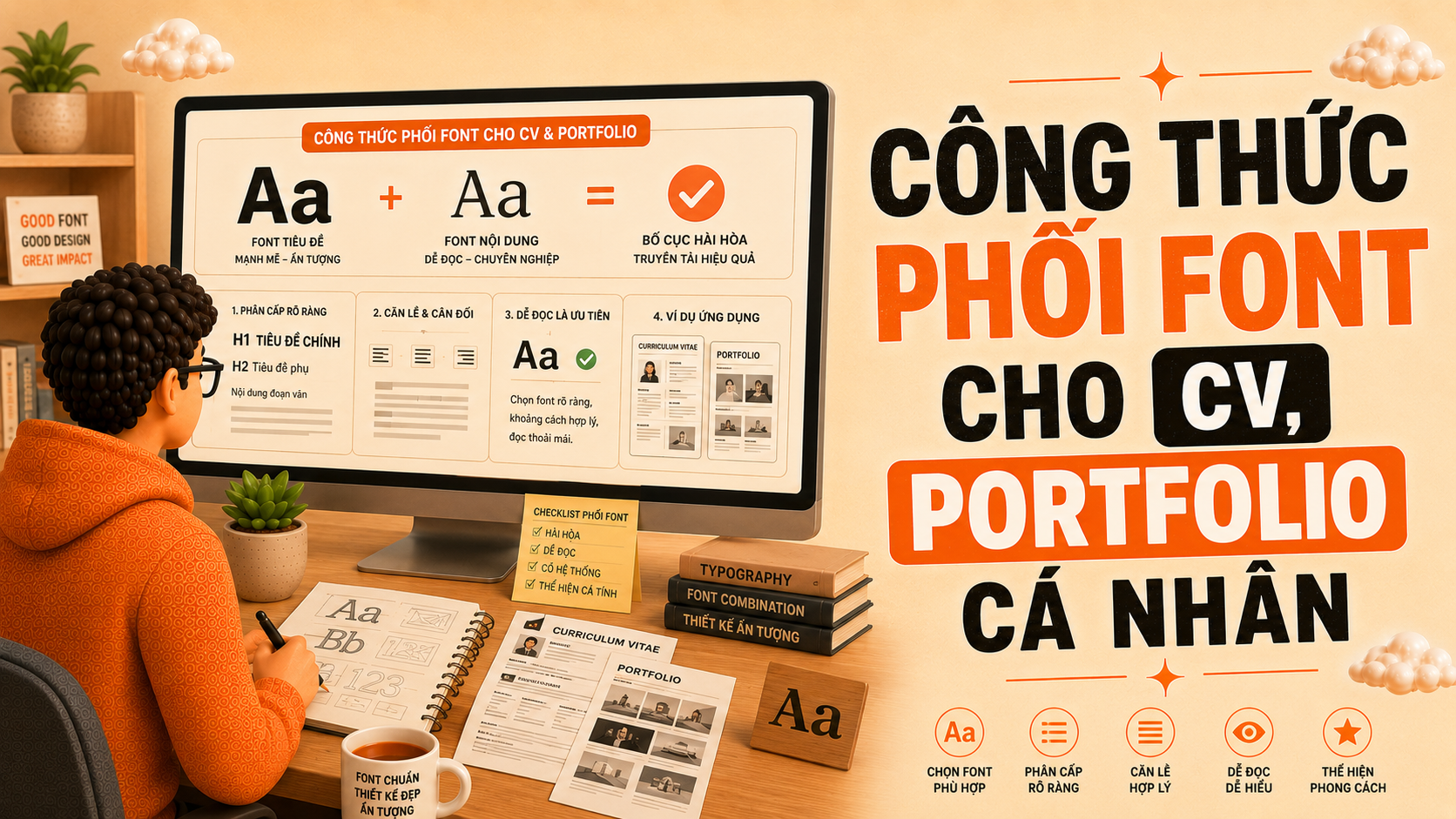
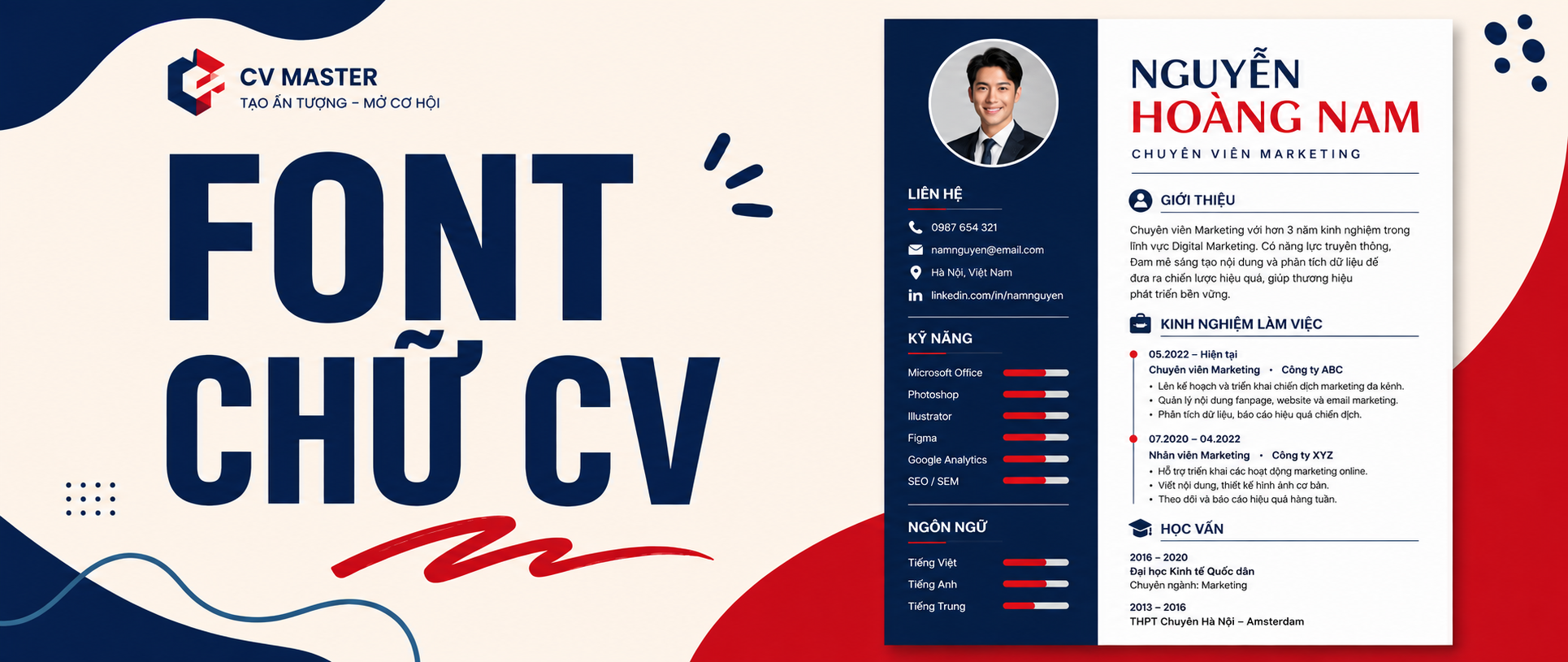
CV và portfolio cá nhân là nơi font chữ ảnh hưởng trực tiếp đến ấn tượng đầu tiên. Nhà tuyển dụng, khách hàng hoặc đối tác thường chỉ mất vài giây để quét tên, vị trí, kinh nghiệm, kỹ năng và các dự án nổi bật. Nếu font khó đọc, quá trang trí hoặc thiếu phân cấp, hồ sơ có thể bị đánh giá kém chuyên nghiệp dù nội dung rất tốt.
Font chữ cho CV, portfolio cá nhân cần cân bằng hai mục tiêu: rõ ràng để người đọc nắm thông tin nhanh, và có cá tính để hồ sơ không bị giống mẫu đại trà. Với CV ứng tuyển, font nên sạch và đáng tin. Với portfolio sáng tạo, font có thể mạnh hơn ở tiêu đề. Với profile chuyên gia, font cần tinh tế và có chiều sâu. Với website cá nhân, font phải đọc tốt trên nhiều kích thước màn hình.
Bài viết này gợi ý các font Việt hóa trên Font S99 phù hợp cho CV xin việc, resume, portfolio designer, hồ sơ freelancer, profile cá nhân, PDF dự án, media kit, website cá nhân và personal branding. Mỗi font được trình bày riêng một dòng kèm anchor Tải về để bạn dễ tải xuống và thử ngay vào thiết kế.
Điểm cần nhớ là CV và portfolio không phục vụ cùng một hành vi đọc. CV thường được quét nhanh để lọc năng lực. Portfolio được xem kỹ hơn để đánh giá gu, quy trình và kết quả. Vì vậy, một bộ font tốt nên có font nền thật rõ cho thông tin, đồng thời có font nhấn đủ cá tính cho phần thương hiệu cá nhân.
Một CV tốt không chỉ đẹp. Nó phải giúp người đọc tìm thấy thông tin quan trọng: bạn là ai, ứng tuyển vị trí gì, có kinh nghiệm nào phù hợp, kỹ năng chính là gì, dự án nào đáng chú ý và cách liên hệ ở đâu. Font đóng vai trò như hệ thống dẫn đường cho mắt.
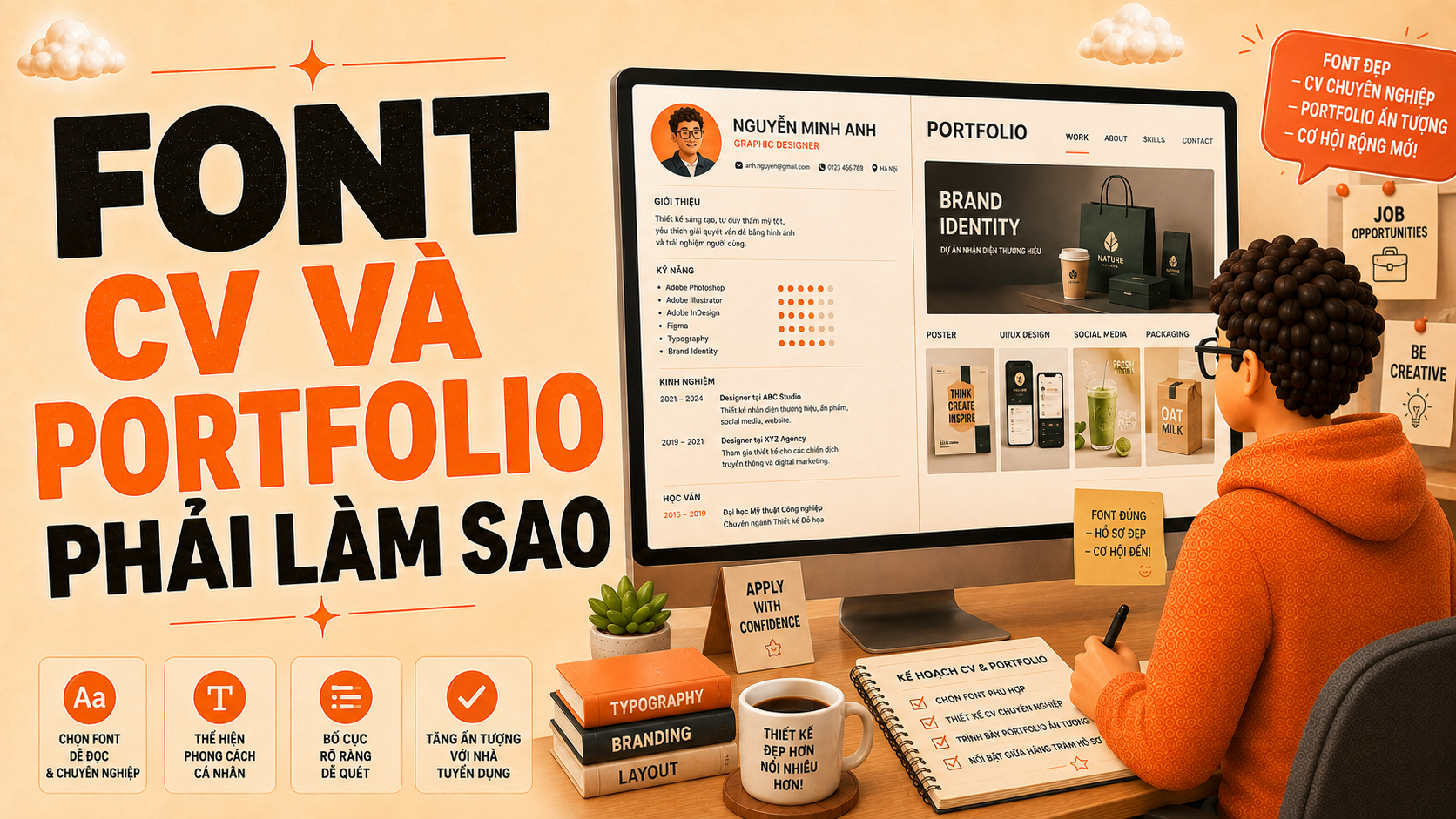
Portfolio cũng vậy. Người xem không đọc từng chữ ngay từ đầu. Họ lướt qua cover, mục lục, case study, ảnh dự án, vai trò của bạn, kết quả đạt được và phần liên hệ. Nếu font tiêu đề thiếu lực, portfolio mất điểm nhấn. Nếu font nội dung khó đọc, case study bị giảm sức thuyết phục.
Với tiếng Việt, font Việt hóa rất quan trọng. Những cụm như kinh nghiệm làm việc, kỹ năng chuyên môn, dự án nổi bật, thành tựu, định hướng nghề nghiệp, xây dựng thương hiệu cá nhân có nhiều dấu. Font lỗi dấu sẽ khiến CV và portfolio mất sự chỉn chu ngay lập tức.
Nếu CV cần đi qua hệ thống lọc hồ sơ hoặc được copy nội dung vào form tuyển dụng, hãy ưu tiên font đơn giản, cấu trúc rõ và hạn chế biến chữ thành hình. Với portfolio PDF hoặc website cá nhân, bạn có thể sáng tạo hơn, nhưng phần thông tin liên hệ, vai trò dự án và kết quả vẫn phải đọc được trong vài giây.
CV thường có nhiều thông tin trong 1-2 trang. Font cần rõ ở cỡ nhỏ, nhất là phần mô tả kinh nghiệm, kỹ năng, thời gian làm việc, tên công ty, mô tả dự án và thông tin liên hệ. Font quá mảnh hoặc quá chặt sẽ làm CV khó đọc.
Một CV hoặc portfolio nên có hệ thống phân cấp: tên cá nhân, vị trí, tiêu đề mục, mô tả, số liệu, link và CTA. Font phải giúp các tầng này khác nhau mà không cần quá nhiều màu hoặc hiệu ứng.
Ứng viên tài chính, nhân sự, vận hành nên dùng font sạch và chuyên nghiệp. Designer, photographer, content creator có thể dùng font cá tính hơn ở headline. Chuyên gia, coach, consultant hoặc manager nên dùng font tinh tế, có cảm giác senior.
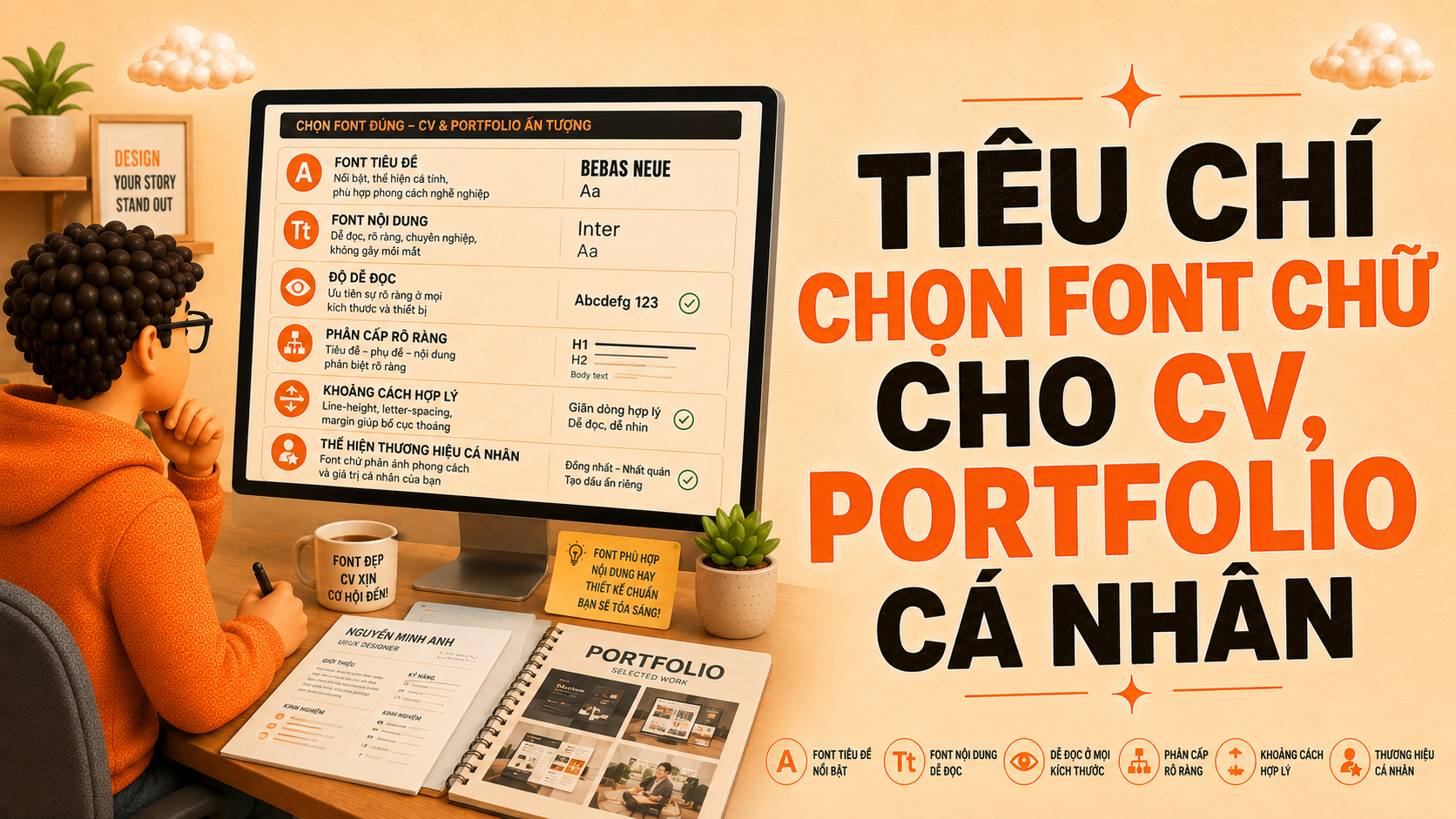
CV thường được gửi dạng PDF, xem trên laptop hoặc điện thoại. Portfolio có thể là PDF, website hoặc link drive. Font cần giữ được độ rõ sau khi xuất file, không lỗi dấu và không bị nặng mắt trên màn hình nhỏ.
Font đẹp không nên lấn át thành tích. Nếu người xem nhớ font nhiều hơn nhớ năng lực của bạn, thiết kế đã đi quá xa. Hãy dùng font như một hệ thống hỗ trợ nội dung: rõ ở phần chính, có nhấn ở điểm cần gây nhớ, và nhất quán từ trang đầu đến trang cuối.
Sans-serif là nhóm an toàn nhất cho CV xin việc. Nó tạo cảm giác sạch, hiện đại, dễ đọc và phù hợp với nhiều ngành nghề: marketing, sales, nhân sự, vận hành, tài chính, giáo dục, công nghệ, chăm sóc khách hàng hoặc quản lý dự án.
Font TH Legacy Sans - Tải về
Font TH Namian Sans Serif - Tải về
Font TH Manisans - Tải về
Font TH Artega - Tải về
Font TH Ervha Regular - Tải về
Font TH Tokyo - Tải về
Font TH Cameo Sans - Tải về
Font UTM Alberta - Tải về
Nhóm này nên dùng cho toàn bộ nội dung chính của CV: mô tả kinh nghiệm, kỹ năng, học vấn, chứng chỉ, thông tin liên hệ và phần giới thiệu ngắn. Bạn có thể dùng bold cho tên vị trí, semibold cho tiêu đề mục và regular cho mô tả để giữ CV gọn nhưng vẫn có nhịp đọc.
Với CV ứng tuyển các vị trí truyền thống, hãy giữ bố cục tối giản. Tên cá nhân có thể lớn hơn, nhưng phần nội dung nên ưu tiên khoảng cách dòng thoáng, tiêu đề mục rõ và không dùng quá nhiều màu. Font sạch sẽ giúp thành tích của bạn nổi bật tự nhiên hơn.
Portfolio cá nhân cần nhiều cá tính hơn CV thông thường. Với designer, marketer, developer, photographer, copywriter, content creator hoặc freelancer, font hiện đại giúp hồ sơ nhìn có thương hiệu hơn, đặc biệt ở cover, section title, case study và website cá nhân.
Font chữ cho CV, portfolio cá nhân tốt phải giúp hồ sơ rõ ràng, có phân cấp và thể hiện đúng cá tính nghề nghiệp. Hãy dùng font sans-serif cho nội dung chính, font hiện đại cho portfolio sáng tạo, font mạnh cho điểm nhấn, font sang cho profile chuyên gia. Quan trọng nhất là font phải Việt hóa tốt, đọc rõ ở cỡ nhỏ và hiển thị ổn khi xuất PDF.